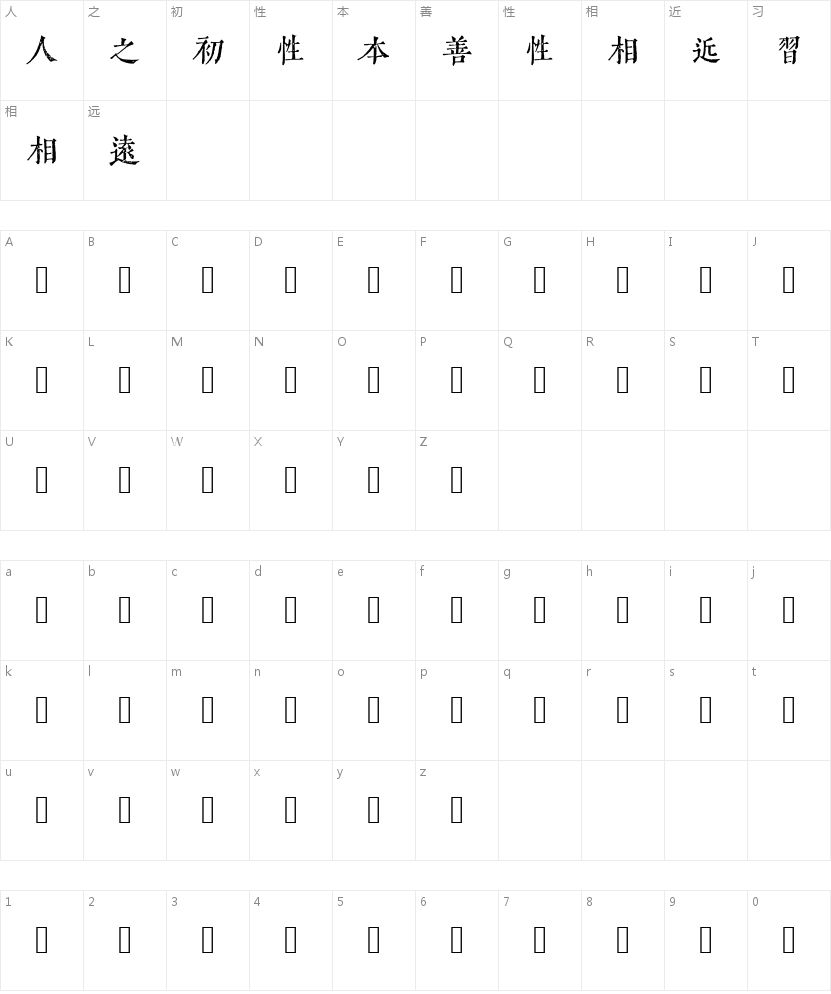
令东齐-伋复刻体-
令东齐-伋复刻体-是一款由令东齐设计的繁体字字体,其中包含了繁体中国文字的传统特色,结合现代技术,令东齐-伋复刻体-拥有更为精细的笔画细节,更加精确的字形,更加完美的字体调整,使得令东齐-伋复刻体-拥有更加优美的外观,更好的可读性。此外,令东齐-伋复刻体-还具备良好的缩放性能,可以支持各种类型的设备和屏幕尺寸,使得字体在不同的设备上都能保持一致的外观和可读性,从而更加方便使用。
令东齐-伋复刻体-是一款非常不错的手写艺术字体,具有很好的视觉感,适合于文化类的宣传设计、商业类品牌的广告和产品包装设计以及个性化文字排版等较多场景。